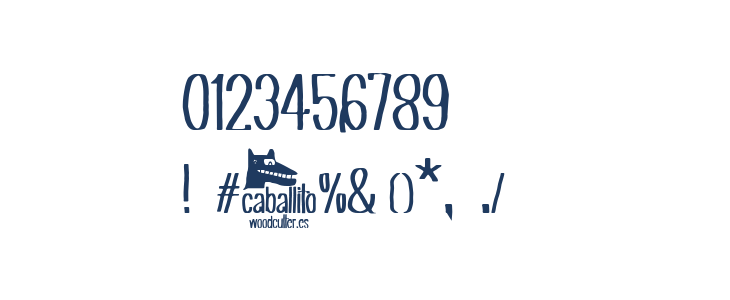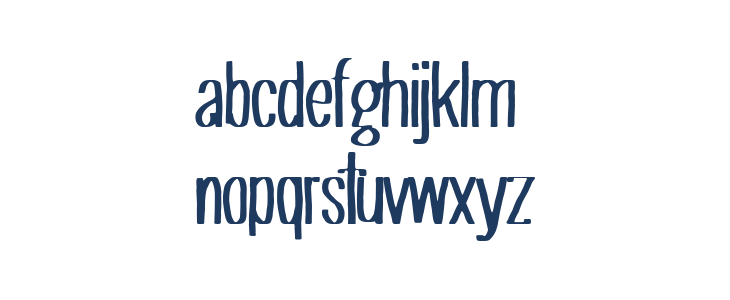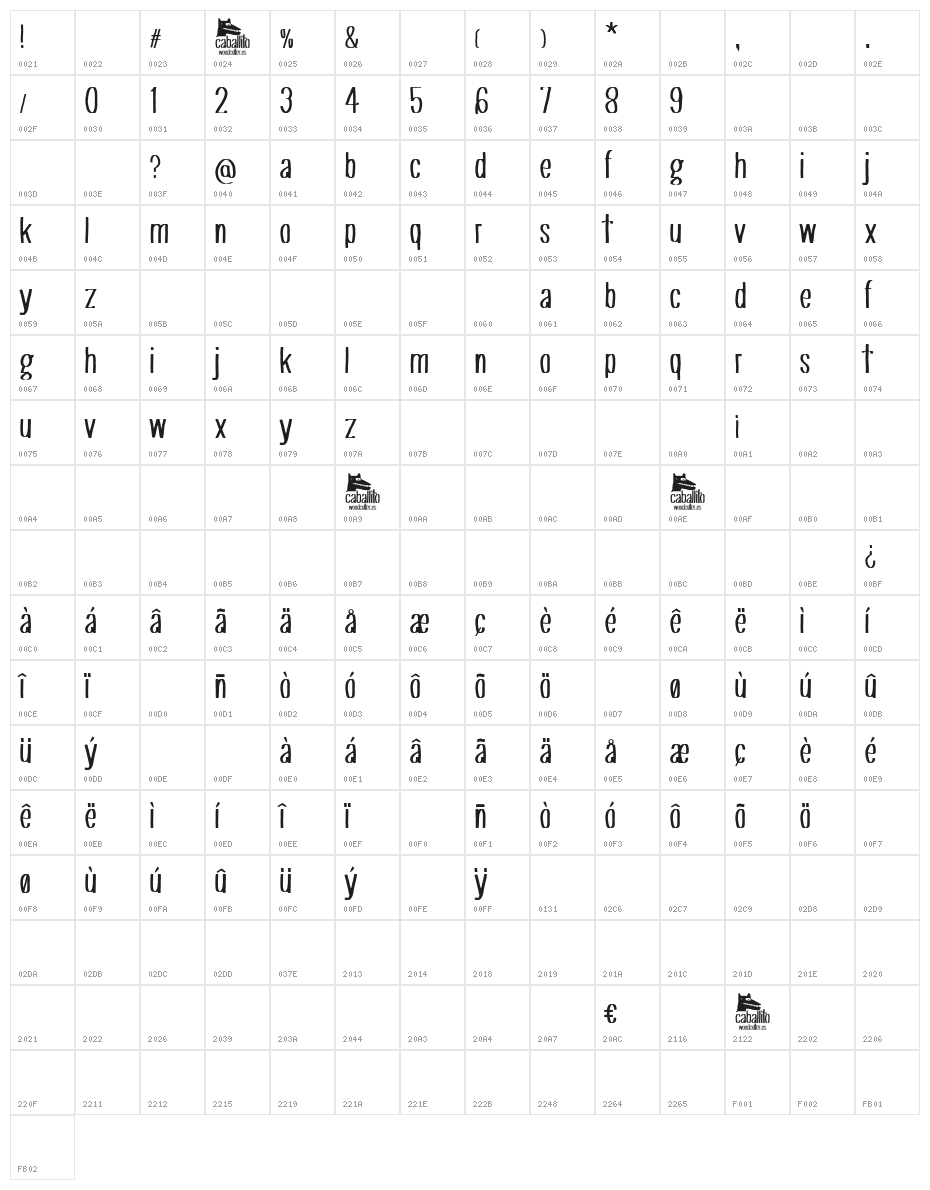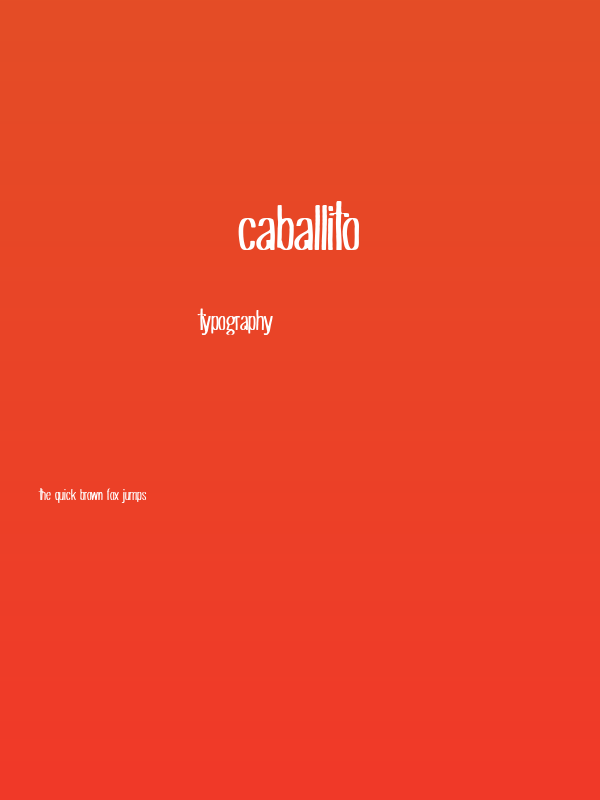
Caballito Font
| Gesamtstil | Playful, Artistic, Informal |
| Anwendungsfall | Headlines, Posters, Branding, Creative Projects |
| Vorgeschlagene Projekte | Children’s books, posters, greeting cards, branding for creative businesses, event invitations. |